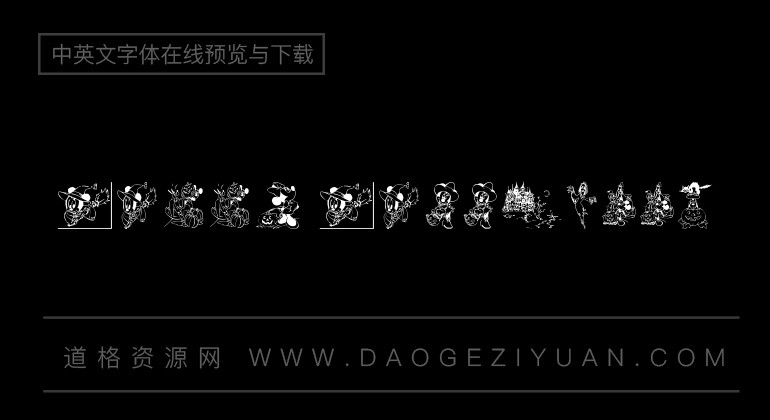
Happy Halloween 字体是一种非常流行的万圣节主题字体,它的特点是字母线条充满了幽默和恐怖的气氛,整体风格非常适合用于万圣节相关的设计和活动中。 这种字体通常采用了黑色或橙色为主色调,字母的造型形态也十分独特,常常带有骷髅、蝙蝠、南瓜头等万圣节常见元素,以及各种诡异的小细节和装饰。 Happy Halloween 字体可以应用于印刷品、海报、贺卡、社交媒体等多种设计中,为万圣节的氛围增添了更多的乐趣和独特性。内容介绍
Happy Halloween是一款非常不错的手写艺术字体,具有很好的视觉感,适合于文化类的宣传设计、商业类品牌的广告和产品包装设计以及个性化文字排版等较多场景。